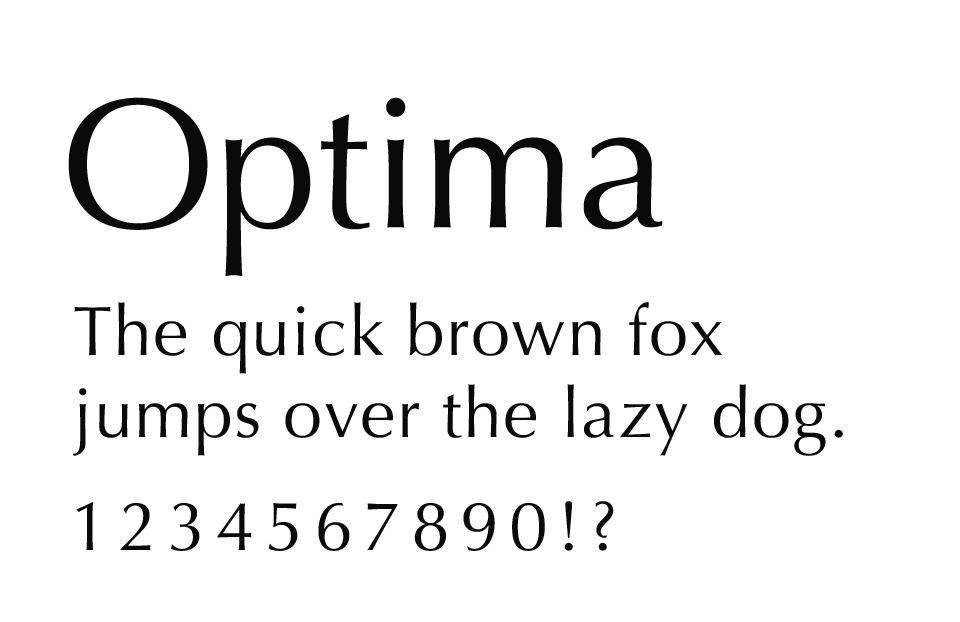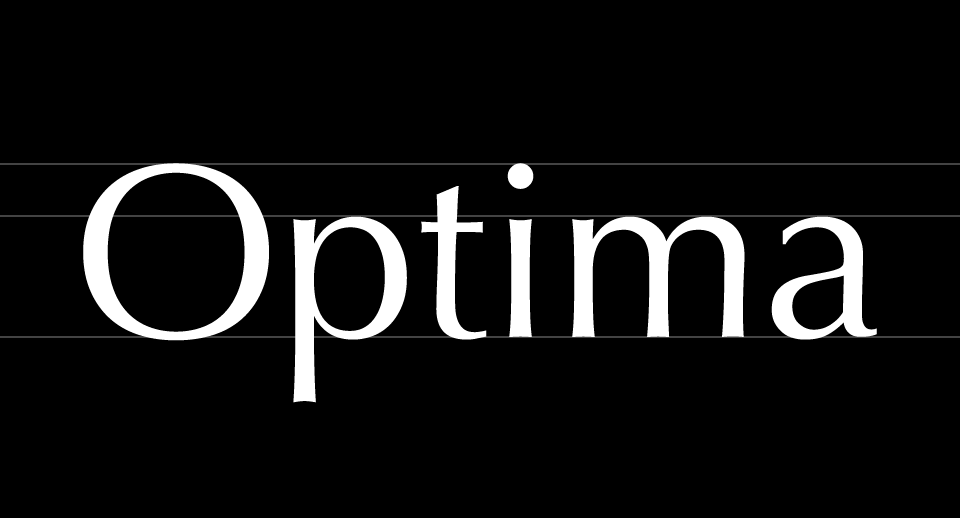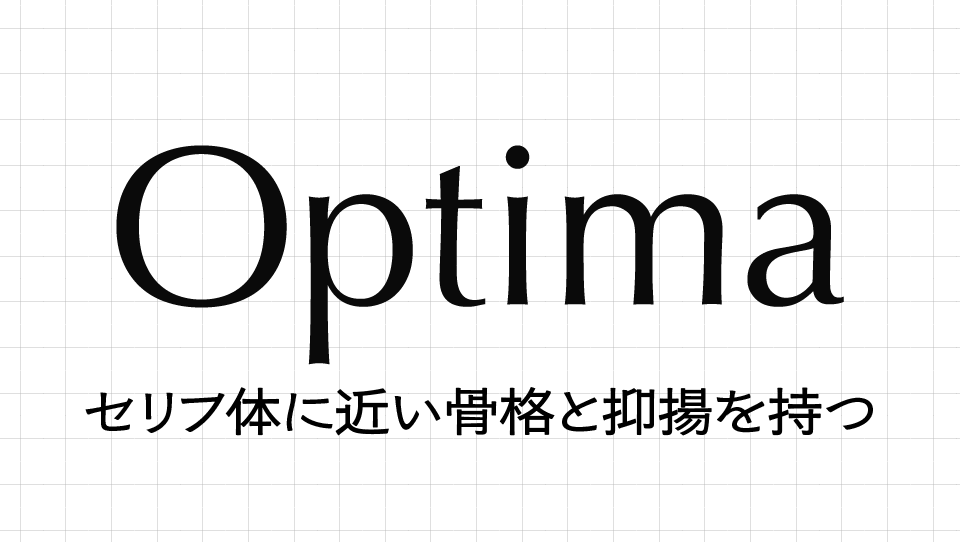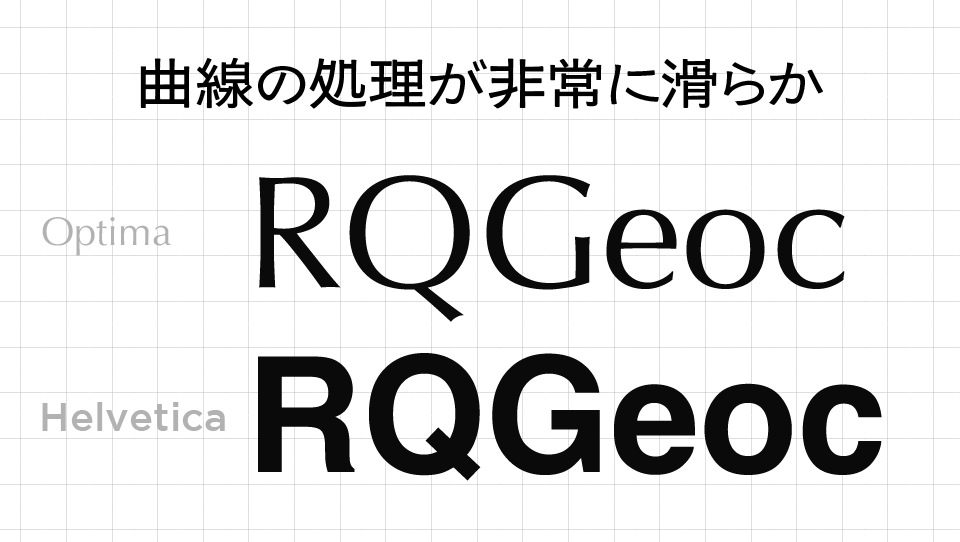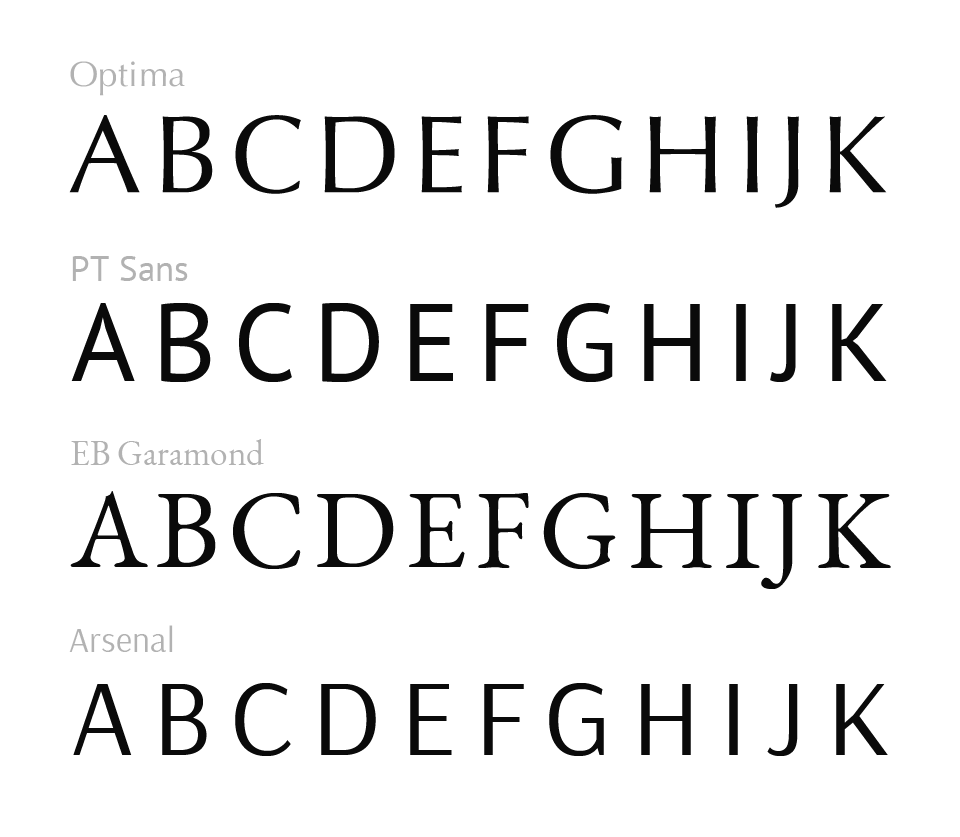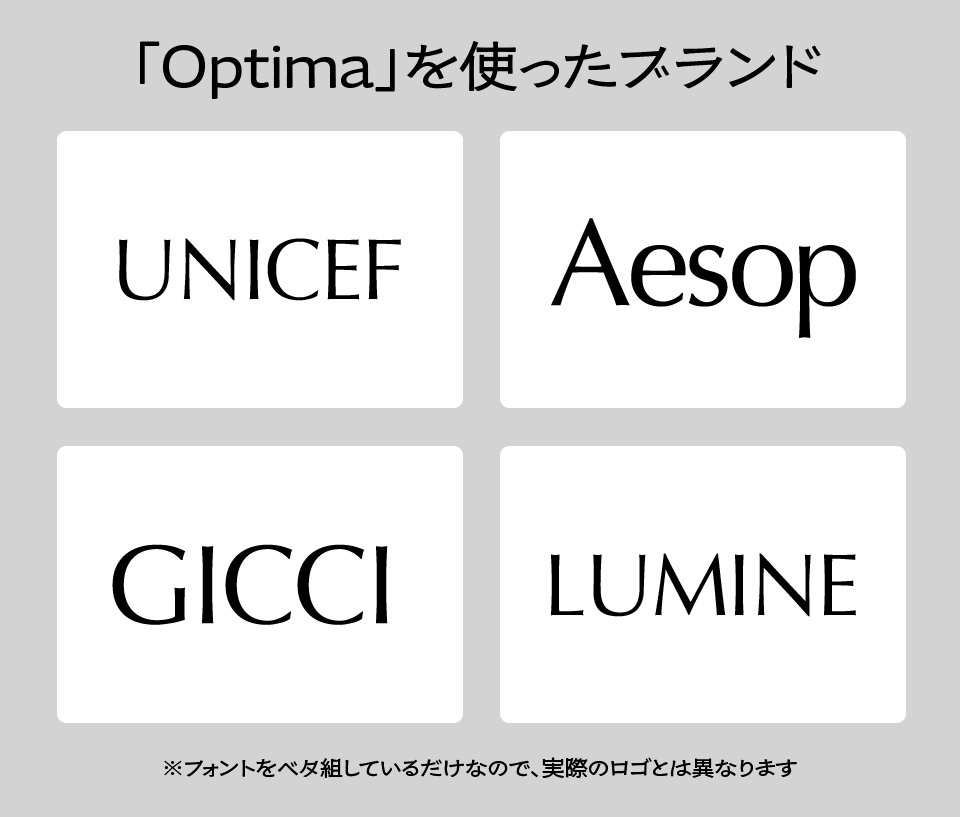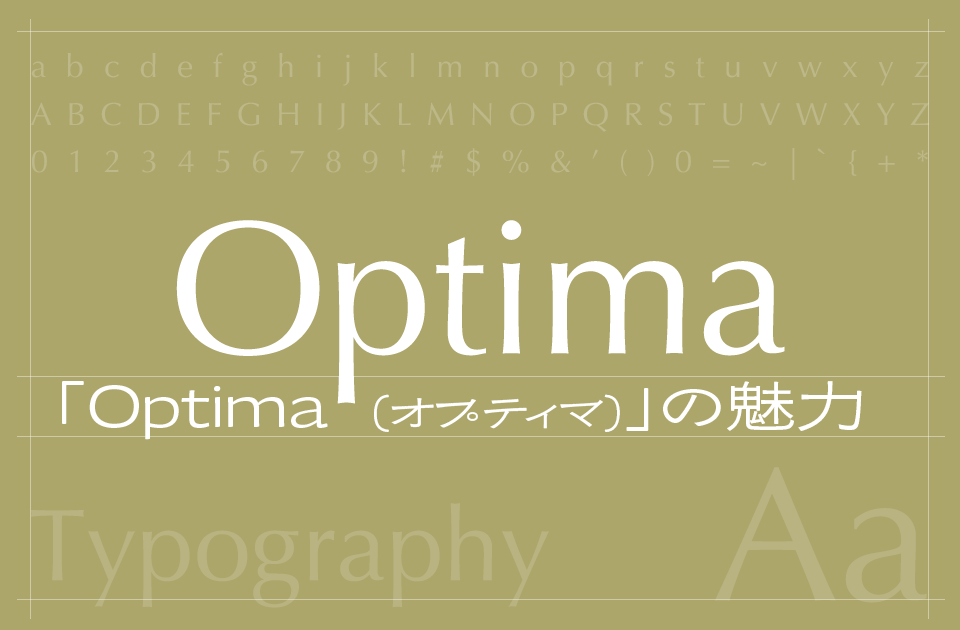
Optima(オプティマ)フォントの魅力とは?クラシックとモダンを兼ね備えた気品ある書体
洗練されていながら、どこかあたたかみがある。クラシックでありながら、現代的な美しさも感じられる——そんな絶妙なバランス感覚を持つフォントが「Optima(オプティマ)」です。
欧文書体の中でも少しユニークな立ち位置にあり、セリフ体ともサンセリフ体とも言い切れないその佇まいは、印刷物やロゴ、装丁、彫刻文字など、幅広いシーンで使われてきました。
この記事では、Optimaの誕生背景から、デザイン上の特徴、代替フォント、採用事例、そしてなぜこのフォントが“静かな強さ”を持つのかをじっくり解説していきます。
Optima(オプティマ)とは
Optimaは、1958年にドイツのタイプデザイナー ヘルマン・ツァップ(Hermann Zapf) によって制作された書体です。発売元はドイツの活字鋳造所「D. Stempel AG」。このフォントの最大の特徴は、一見するとサンセリフ体に見えるにもかかわらず、セリフ体に近い骨格とリズムを持っていることです。
つまり、セリフ(飾りのある線)こそ省かれているものの、文字の形や抑揚、筆の流れを感じさせるストロークが、セリフ体に近い雰囲気を醸し出しているのです。これにより、モダンさと古典的な優雅さの両方を兼ね備える、独自のタイポグラフィが生まれました。
Optimaの歴史と背景
ヘルマン・ツァップは、Optimaをデザインするにあたり、ローマ時代の碑文文字(ローマンキャピタル)からインスピレーションを得たと言われています。実際、Optimaの大文字には、碑文に見られるような洗練されたカーブや、細やかな太さのコントラストが見て取れます。
1950年代は、幾何学的サンセリフ体(Futuraなど)やグロテスク体(Helveticaなど)が台頭していた時代ですが、その中でOptimaは柔らかく人間味のあるサンセリフ体として、独自の存在感を放ちました。
のちにAdobeやApple製品のフォントとしても採用され、グローバルに広まっていきます。
Optimaの特徴
Optimaは、サンセリフ体のように見えて、実はセリフ体に近い骨格と抑揚を持つという、非常にユニークな書体です。ストロークの太さにはわずかなコントラストがあり、縦線と横線が完全に均一ではありません。これはセリフ体特有の“筆の流れ”や“文字のリズム”を感じさせ、読者にやわらかく自然な印象を与えます。
さらに、曲線の処理が非常に滑らかで、文字のアウトライン全体に有機的な美しさが漂います。一方で、セリフが付いていないことで視認性やモダンさも確保されており、古典と現代のちょうど中間にあるようなタイポグラフィになっています。洗練されつつも、冷たさを感じさせない——それがOptimaの最大の魅力と言えるでしょう。
Optimaの類似・代替フォント
以下のようなフォントが、Optimaの代替として挙げられます
- Candara(Microsoft Office)
Optimaに似たストロークと丸みを持ち、ややカジュアルな印象。 - Source Sans Pro
ややサンセリフ寄りですが、Optimaのような中立性を持つ。 - EB Garamond(GoogleFonts/AdobeFonts)
セリフ付きだが、Optimaの持つクラシカルな雰囲気に近い。 - PT Sans(GoogleFonts)
端正な字形で、UI用途でも扱いやすい。 - Aesenal(GoogleFonts)
Optimaと比較すると長体フォルムになっている。
Optimaが採用された代表的な事例
Optimaは、その高貴さと洗練された印象から、信頼性・伝統・品格を打ち出したいブランドやプロジェクトに多く採用されています。
- ユニセフ(UNICEF)
かつてキャンペーン資料にOptimaを採用されていました。 - Aesop(イソップ)
オーストラリアのメルボルン発のスキンケアブランドのロゴタイプに使われています。 - GUCCI(グッチ)
イタリアの高級ファッションブランド「グッチ」のロゴタイプのベースフォントとして使われています。 - LUMINE(ルミネ)
日本のショッピングセンター「ルミネ」のロゴタイプのベースフォントとして使われています。 - ヴィクトリア&アルバート美術館(V&A)
展示資料やサインにOptimaが使用され、クラシックと現代の融合を体現。 - 多くの墓碑・記念碑
ローマ碑文風の美しさが評価され、墓石や記念モニュメントにも多数使われています。
Optimaは、静かに語りかけてくる“気品のある声”のようなフォント
声高に何かを訴えたり、目立とうとしたりするわけではない。それでもOptimaの文字は、見る人の心にじんわりと残ります。
派手さや尖りを抑えつつ、確かな存在感と、品のある佇まいで語りかけてくる。そんな“静かな強さ”がこのフォントには宿っています。
クラシックな美しさと、現代的な使いやすさ。その両方を備えたOptimaは、どんな時代にも寄り添ってくれる柔らかな存在です。もしあなたが「落ち着いた印象で、確かな信頼感を届けたい」と思ったとき、Optimaはきっとその願いに応えてる書体です。